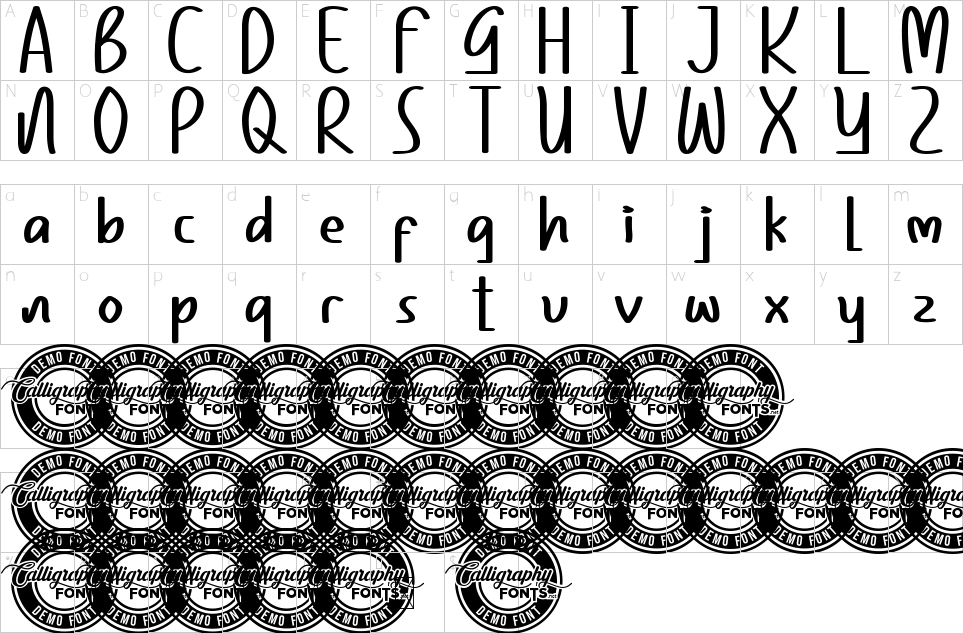
Grand Auto Font – Download Grátis
Descubra Grand Auto, uma elegante fonte grátis que complementará perfeitamente seus projetos digitais. Desenvolvida por CalligraphyFonts, esta fonte é ideal para quem busca um estilo moderno e sofisticado. Com seu design minimalista mas atencioso aos detalhes, a Grand Auto vai dar o toque final à sua marca ou projeto. Através de suas 2,748 downloads, você pode perceber que os criadores estão realmente se preocupando com a qualidade deste recurso fonte. Seja para websites, logotipos ou qualquer outro tipo de criação digital, Grand Auto oferece precisão e facilidade ao usar. Sem dúvida, é uma opção ideal para quem busca uma solução sem custo adicional para um elemento crucial como a fonte na sua identidade visual.